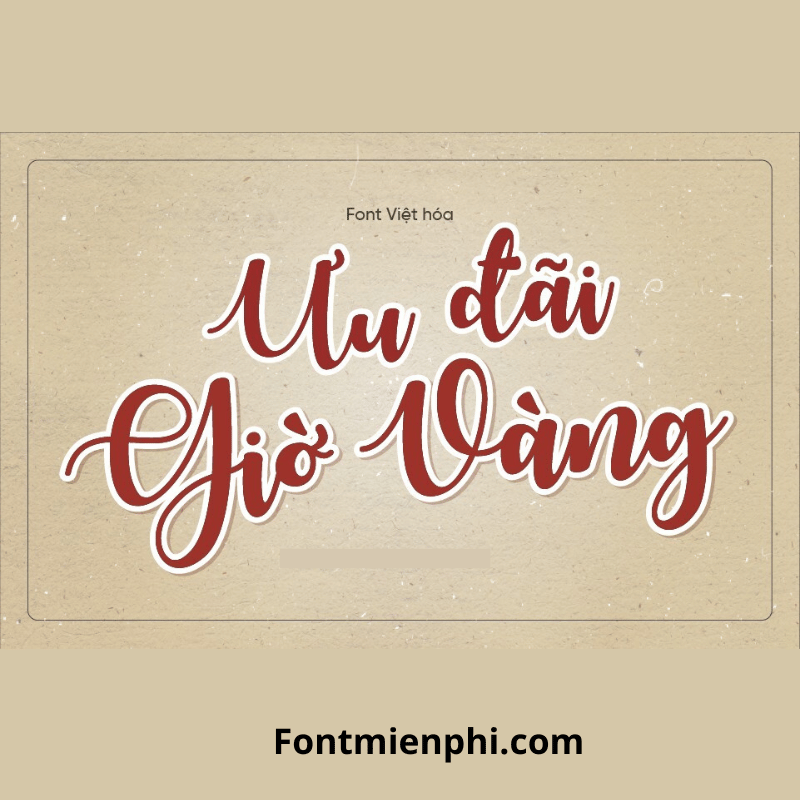
Font Việt hóa 1FTV VIP Autumn in November
Font Việt Hóa 1FTV VIP Autumn in November – Nét Chữ Mùa Thu Sang Trọng
Giới thiệu
Font Việt hóa 1FTV VIP Autumn in November là bộ font chữ nghệ thuật cao cấp, được thiết kế tinh tế với cảm hứng từ mùa thu dịu dàng. Với đường nét mềm mại, thanh lịch, font chữ này phù hợp cho thiết kế in ấn, bìa sách, thiệp mời, logo và dự án sáng tạo. Đặc biệt, font hỗ trợ đầy đủ tiếng Việt, giúp người dùng dễ dàng ứng dụng trong mọi ấn phẩm.
Đặc điểm nổi bật
• Phong cách sang trọng: Nét chữ uốn lượn nhẹ nhàng, mang đậm hơi thở mùa thu, tạo điểm nhấn ấn tượng.
• Hỗ trợ tiếng Việt: Đầy đủ dấu và ký tự đặc biệt, tương thích với mọi phần mềm thiết kế.
• Đa dạng ứng dụng: Dùng cho branding, quảng cáo, thiệp cưới, bao bì sản phẩm.
• Chất lượng VIP: Độ sắc nét cao, không lỗi font khi in ấn hoặc hiển thị kỹ thuật số.
Kết luận